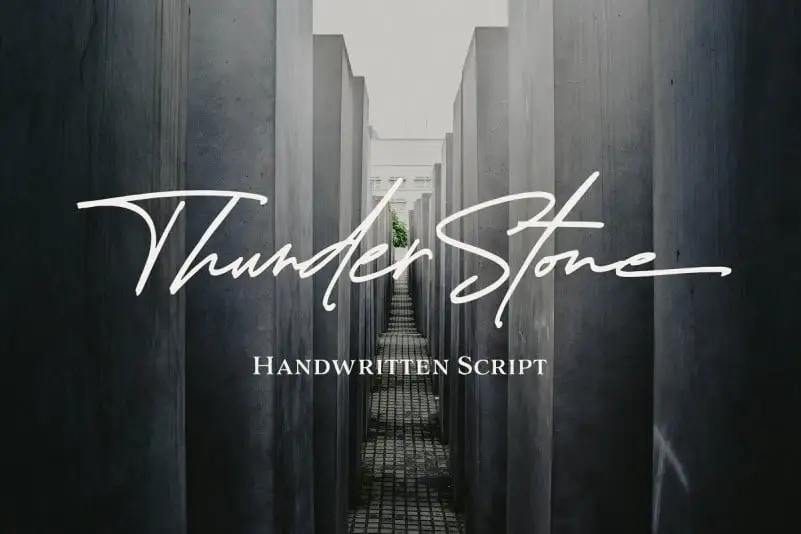
Thunder Stone Handwritten Font é uma fonte cursiva casual e elegante criada pela Get Studio. Perfeita para diversas necessidades de design, essa fonte se destaca por sua harmonia tipográfica perfeita para projetos profissionais que incluem logomarcas, identidade visual, revistas, posts de blog, mídias sociais, citações e designs publicitários. Seu charme natural a torna ideal para expressar um toque pessoal em seus projetos, seja para criar uma assinatura única para sua marca ou adicionar autenticidade aos textos dos seus materiais digitais. Experimente Thunder Stone Handwritten Font para dar vida a suas criações e enriquecer seu design.